もっちりぽってり「イワタ福まるご」
これまでになかった、有機的な曲線で構成された新しい丸ゴシック体です。
ノーマルな丸ゴシックでは物足りないが、ポップ書体では強すぎる、そんなときの新しい選択肢になれる書体。見出しから、しっかり文字組までこなせます。
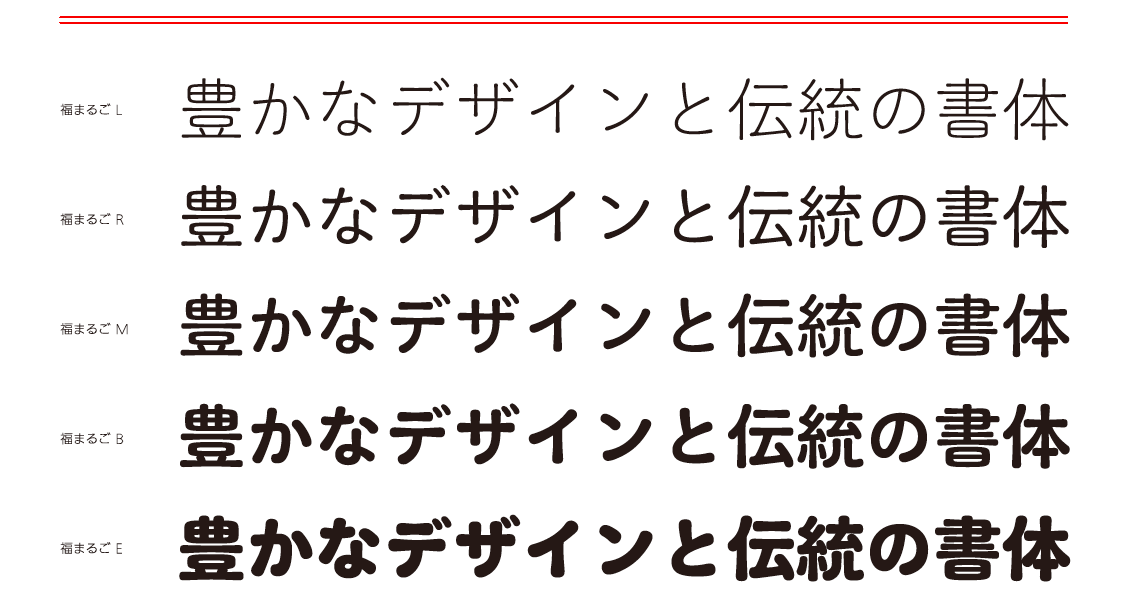
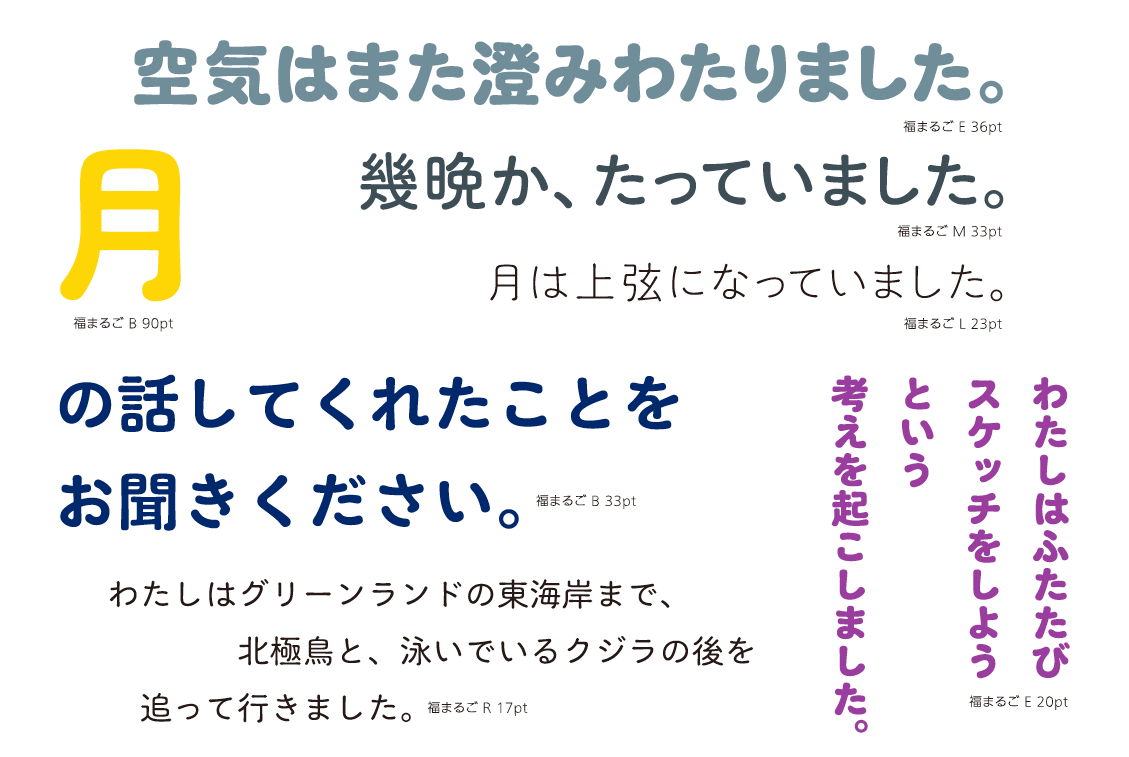
「 イワタ最太、大迫力」の明朝体「イワタ超明朝U」
明朝体の訴求力を最大限に追求した「イワタ超明朝U」。重厚感溢れるウエイトを支える骨格も一から新たに開発。明朝体でなければできない表現を可能にしました。
さらに読みやすさを追求した「イワタ横太明朝体オールド」
可読性の高さで定評がある「イワタ明朝体オールドをさらに読みやすく」をテーマにデザイン。横線を太め、細部にこだわり、電子媒体でも読みやすくしました。